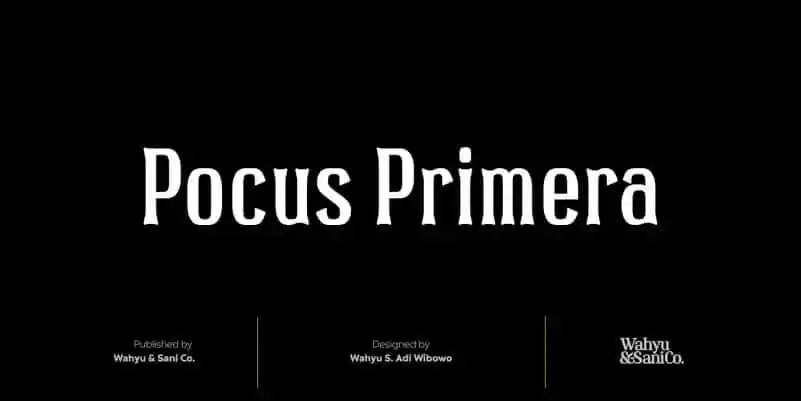
A Pocus Primera Serif é uma fonte séria elegante criada por Wahyu & Sani Co., perfeitamente adaptada para projetos publicitários e de outdoors. Esta fonte combina a sofisticação dos estilos romanos modernos com o encanto da tipografia celta, resultando em um design que transmite elegância e classe sem perder seu charme original. Essa fonte vem em duas versões: uma básica e outra desafiada, adaptadas para suportar a maioria das línguas romanas europeias. Completam o pacote as letras maiúsculas e minúsculas, sinais de pontuação e alguns símbolos matemáticos, garantindo que você tenha todos os elementos necessários para personalizar seus materiais impressos. Uma fonte como esta é perfeita para flyers publicitários ou qualquer projeto que exija uma aparência sofisticada. A Pocus Primera Serif é uma escolha ótima para quem busca uma tipografia elegante e atemporal, sem abrir mão de seu design moderno e atraente. Não espere mais – invista em sua identidade visual com essa bela fonte.